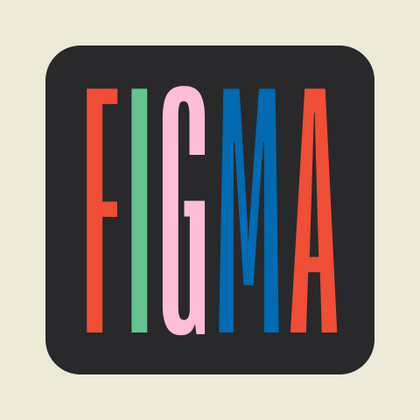
Шрифты для Figma
Для профессиональных дизайн-систем в Figma требуются шрифты для Figma, которые корректно работают с авто-лейаутом и компонентами. Каталог TypeType предлагает гарнитуры с идеальными кернинг-парами, четким рендерингом в режиме реального времени и поддержкой переменных настроек — идеальный выбор для дизайнеров интерфейсов.
TT Norms® Pro — TT Нормс Про
TT Commons™ Pro — TT Коммонс Про
TT Hoves Pro — ТТ Ховс Про
Произносится «ТТ Ховс Про». «Hoves» — производное слово от horizontal (с английского «горизонтальный») и vertical (с английского «вертикальный»). «Pro» произносится как «про», и является разговорным сокращением слова «профессиональный». Буквы «TT» являются аббревиатурой названия компании.
TT Norms® Pro Serif — TT Нормс Про Сериф
TT Livret — ТТ Ливрет
Произносится «ТТ Ливрет». «Livret» — производное слово от le livret, в переводе с французского «книжечка». Буквы «TT» являются аббревиатурой названия компании.
TT Polihaus — ТТ Полихаус
Произносится «ТТ Полихаус». «Polihaus» — производное от греческого «πολύς», в переводе — «много», и слова «хаос». Буквы TT являются аббревиатурой названия компании.
TT Polihaus — экспериментальный гротеск, который на первый взгляд кажется обычным, а затем разбирается на части, превращаясь в трафаретный узор.
TT Nooks Serif — ТТ Нукс Сериф
Произносится «ТТ Нукс Сериф». «Nooks» — производное слово от nook, в переводе с английского «закоулок». «Serif» произносится как «сериф», в переводе с английского «антиква». Буквы «TT» являются аббревиатурой названия компании.
TT Nooks Serif — акцидентная новостильная антиква с лёгким налётом эгоцентричности. У неё острый и твёрдый, при этом элегантный и статный характер.
TT Chocolates — ТТ Чоколитс
Произносится «ТТ Чоколитс». «Chocolates» — производное слово от chocolate, в переводе с английского «шоколад». Буквы «TT» являются аббревиатурой названия компании.
TT Chocolates — изящный гуманистический гротеск сo сбалансированными пропорциями, близкими к классическим. Шрифт с приятным дружелюбным характером, который интуитивно воспринимается как что-то знакомое.
TT Nooks Script — ТТ Нукс Скрипт
Произносится «ТТ Нукс Скрипт». «Nooks» — производное слово от nook, в переводе с английского «закоулок». «Script» произносится как «скрипт», в переводе с английского «курсив». Буквы «TT» являются аббревиатурой названия компании.
TT Nooks Script — шрифт с уникальным рисунком, который не имеет прямых аналогов.
TT Qurdisma — ТТ Курдизма
Произносится «ТТ Курдизма». Слово «Qurdisma» происходит от греческого κούρδισμα, в переводе — «извилистый». Буквы TT являются аббревиатурой названия компании.
TT Qurdisma — узкий и плотный декоративный шрифт, напоминающий причудливое растение. Вьющиеся, плавные контуры рождают растительный орнамент.
TT Neoris Pro — ТТ Неорис
Произносится «ТТ Неорис». «Neoris» — производное слово от neo («новый» с латинского) и rise («восход» с английского). Буквы «TT» являются аббревиатурой названия компании.
TT Firs Neue — ТТ Фирс Нью
Произносится «ТТ Фирс Нью». «Фирс» — производное слово от fir, в переводе с английского «ель». «Neue» — в переводе с немецкого «новый». Буквы «TT» являются аббревиатурой названия компании.
TT Firs Neue — скандинавский гротеск, сочетающий выразительные графические элементы с универсальностью использования. Мы проанализировали каждый контур и графический элемент. Пересобрали шрифт заново, чтобы сохранить лучшее и исправить необходимое.